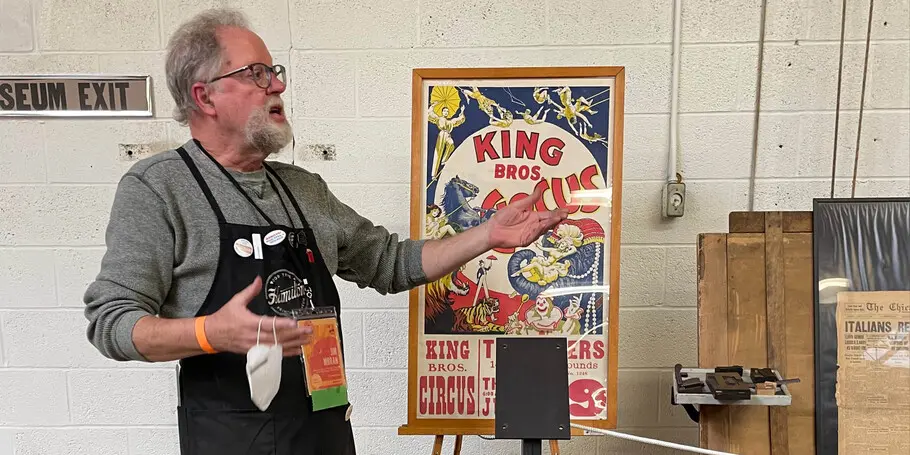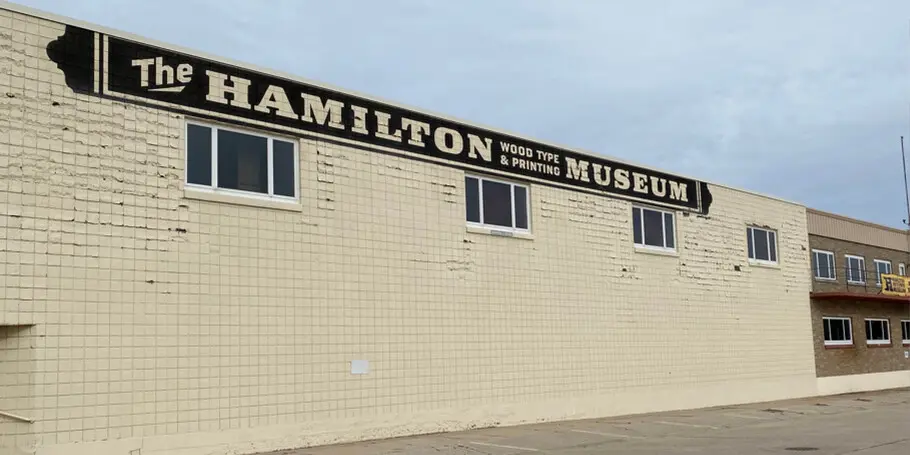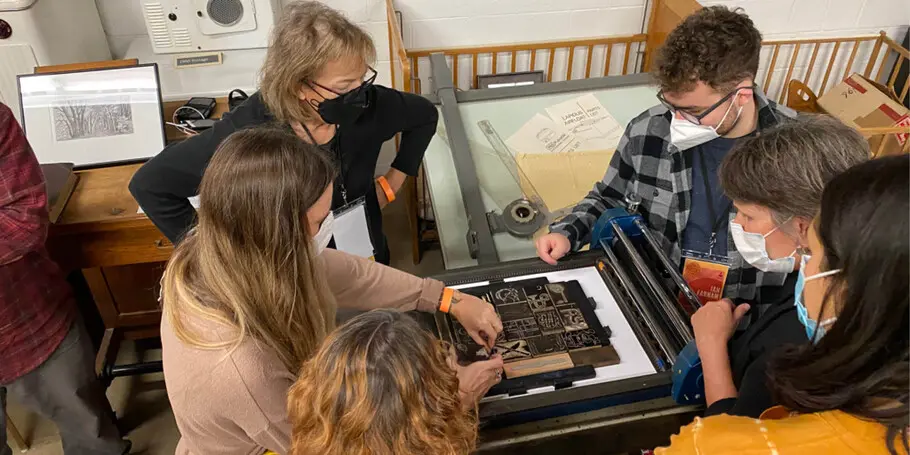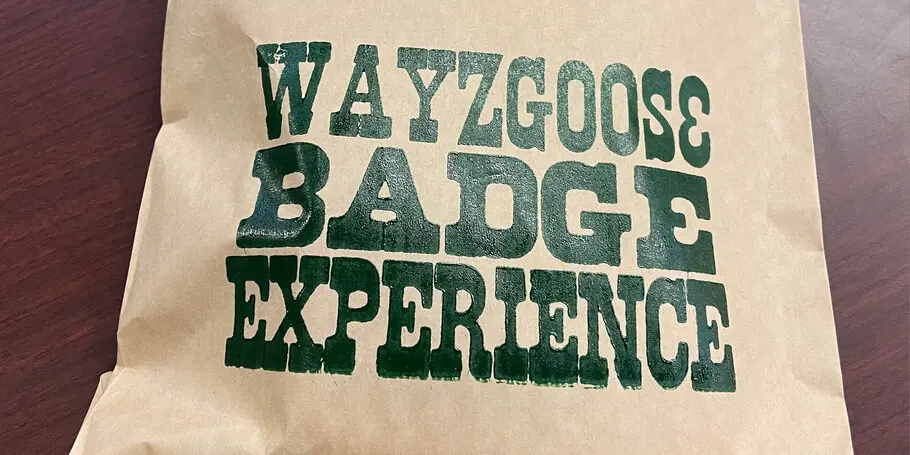
Creative Characters S3 E1: Jim Moran, Bewahrung der Druckgeschichte im Hamilton Wood Type & Printing Museum.
„ Meiner Ansicht nach liegt der wahre Wert darin, die Hände aktiv zu beschäftigen, sie schmutzig zu machen und Dinge herzustellen: Das taktile Erlebnis des fertigen Produkts, gedruckt in Holzlettern, ist wirklich aufregend. “
Jim Moran.
Jim Moran Hamilton Wood Type
Das Hamilton Wood Type Museum befindet sich in einem alten Fabrikgebäude in Twin Rivers, Wisconsin, am Ufer des Michigansees. Das Haus widmet sich der Herstellung von Plakatschriften und beherbergt die weltweit größte Sammlung von Schriften und Werkzeugen – von den Maschinen bis zu den Druckpressen. An Workshop-Tagen kann man den Druckern bei der Herstellung von Probeabzügen zuschauen.
„Die 1880 gegründete Hamilton Wood Type Manufacturing Corporation ist eines der wichtigsten Unternehmen in der grafischen Industrie. Holzlettern waren damals im Bereich des Plakatdrucks von entscheidender Bedeutung. Wenn man große Texte setzen wollte, war es leichter und praktischer, sie aus Holz zu schneiden, anstatt Metallformen zu bauen und sie zu gießen.“
Moran beschreibt die Sammlung der Holzblockbuchstaben mit einem tiefen Gefühl der Wertschätzung. „Wenn wir [das Museumserlebnis] in Flaschen abfüllen könnten, würde es sich gut verkaufen, zumindest an Liebhaber der Druckkunst: Es riecht wunderbar nach Druckfarbe und Spiritus, besonders in meiner Abteilung. Wir haben sehr viele Schriften ausgestellt. Während sie nach dem Herstellen sehr blass aussahen, haben sie über die Jahre Patina angesetzt, was wunderschön aussieht. Es gibt eine Unmenge an Schattierungen von Braun über Kastanie bis zu Mahagoni.
Im Herbst veranstaltet das Museum das jährliche Wayzgoose-Festival, eine Konferenz für Druck- und Designexperten aus aller Welt. „Was mir daran gefällt, ist, dass man auf der Veranstaltung sowohl ältere Leute als auch 20-jährige Studierende antrifft, die gerade erst begonnen haben, Design- oder Typografie-Kurse zu belegen. Auch die Tatsache, dass sich die Hälfte des Publikums jedes Jahr wieder erneuert, finde ich wunderbar.“
Beim Nachdenken über die Natur der Holzdrucks wird Moran immer wieder bewusst, dass uns diese Technik in vielerlei Hinsicht zu dem zurückführt, wofür der Körper geschaffen ist, nämlich aktiv zu sein. Es ist ein mühsamer Prozess, eine Buchdruckmaschine für Holzlettern einzurichten.
Er weist auch darauf hin, dass die Beschäftigung mit der historischen Drucktechnik den Kreativen eine dringend benötigte Pause von digitalen Bildschirmen verschafft, was im heutigen digitalen Zeitalter viel zu selten vorkomme.